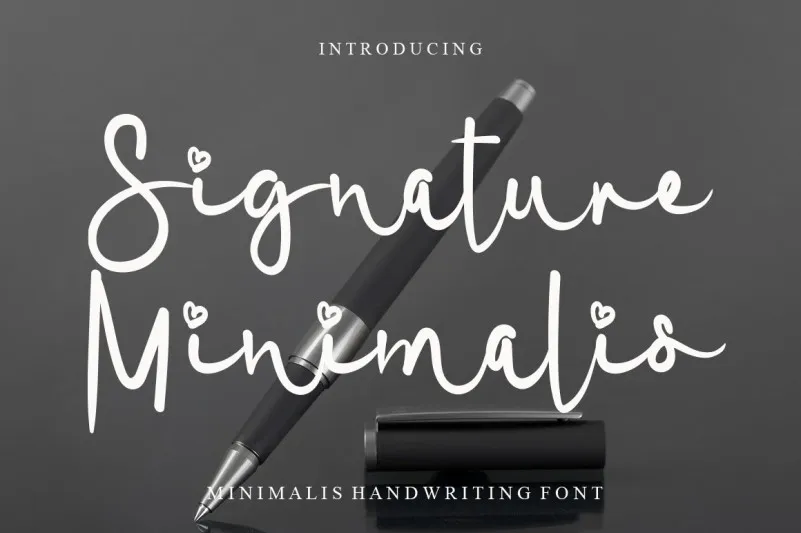
Signature Minimalis Font – Download Grátis
Esta é uma fonte escrita a mão com destaque mais intenso do que as fontes normais. Sua personalidade única a torna perfeita para projetos que exigem um toque criativo e imponente. Ideal para identidades digitais, capas de livros ou qualquer outro projeto que deseje destacar sua presença. Com uma designer talentosa como Levincreative à frente desta fonte, é fácil ver que ela não é apenas uma opção versátil, mas também muito personalizada. A assinatura Minimalis Font é perfeita para quem busca uma escrita a mão com um toque moderno e minimalista, criando assim um contraste interessante entre o formato digital e a personalização visual. Engane-se se pensar que apenas escritas em texto simples, essa fonte oferece variedade suficiente para tornar qualquer projeto único e memorável.